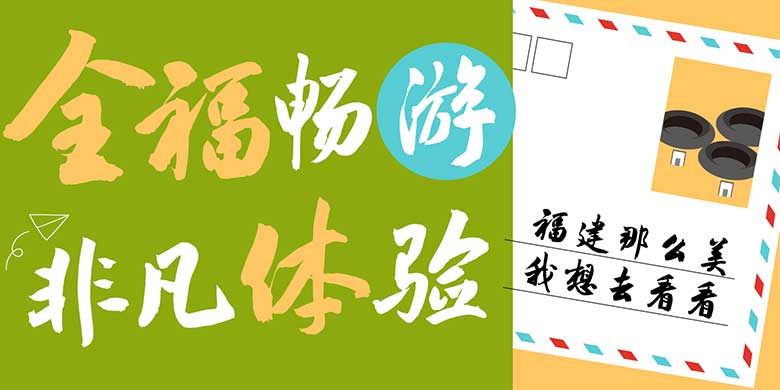
方正全福体是方正首款区域性定制字体,也是国内首款由省级政府文旅管理部门定制的字体,“全福体”将福建独特的特征和记忆点融入字体的一笔一画间,可应用于各类传播媒介和公共空间,在城市形象宣传和推广方面都将产生微妙却不可小觑的影响力,欢迎喜欢方正全福体的朋友前来下载使用。
为了更好地塑造福建的区域形象,体现福建文化旅游资源的丰富性与独特性,凸显“全福游、有全福”品牌,福建省文化和旅游厅与方正字库联合推出福建文旅厅系统专属定制字体——“全福体”,这是方正首款区域性定制字体,也是国内首款由省级政府文旅管理部门定制的字体。
全福体”是一款书法行书字体,由来自福建福州的方正字库设计总监仇寅书写设计。仇寅早在80年代就已享誉中国硬笔书坛,出版有《仇寅钢笔字》、《仇寅书外国名诗》、《古帖新临多体钢笔字帖》等多部字帖。加入方正字库后,创作出了方正大魏体、方正悠黑等多款蕴含书法底蕴、书写人文精神的字体。2017年起,仇寅担任中华精品字库工程设计总监,指导整理并创写设计了方正苏轼行书、方正米芾行书、方正赵孟頫楷书等多款精品书法字体。
“全福体”的设计,继承了“全福游,有全福”原始LOGO的厚重和毛笔书写韵律,受福建山水人文浸润三十多年的仇寅,在书写设计过程中,融合了宋代“尚意”书风的格调,并考虑字库的易识性、通用性,进行了多次书写尝试及优化调整,最终完稿的“全福体”给人以文雅、厚重、大气之感,雅俗共赏。